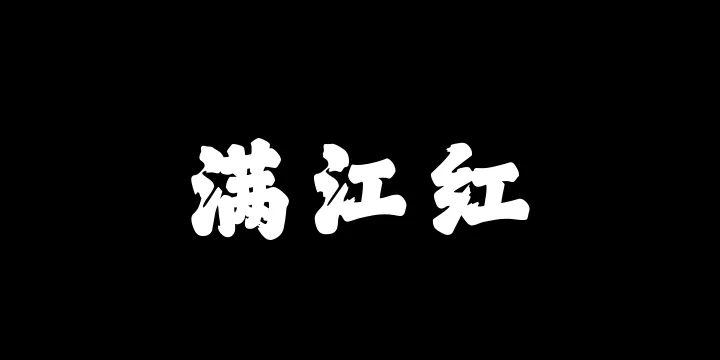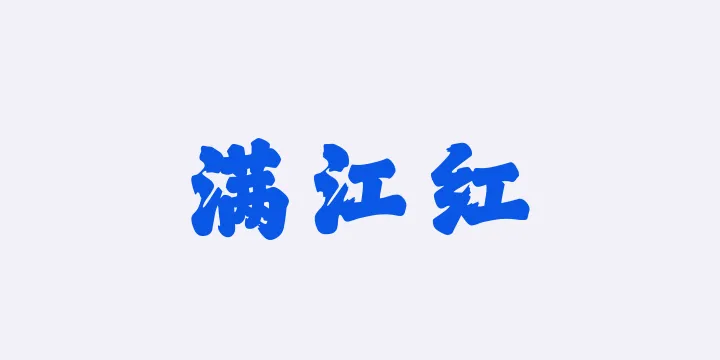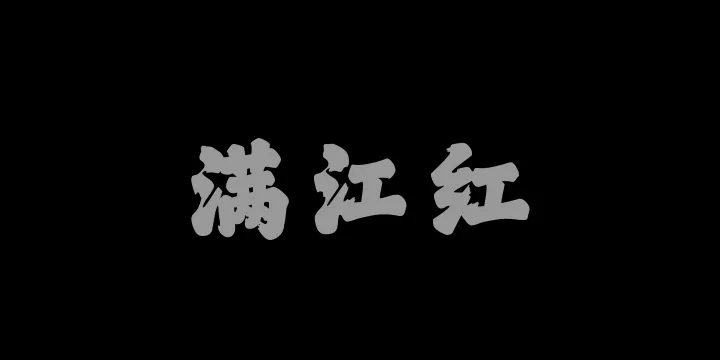
字体全名: 山海满江红W
字体简介: 山海满江红,是一款擘窠大字榜书字体。包含简繁汉字9169个。该字体雄健有力,霸气外露,在粗细的纵横间,拥有非常规的张力特性。该字体的笔画充满力量感,组合搭配极富强烈的节奏感,融入楷书特点,飞白纵横其间,使字体的视觉效果有力、宽厚、方正,充满了稳重感和设计感。笔画与字形间透露着榜书的古雅和刚劲的特点,在浑厚的同时而又极富张力,桀骜不驯的特性,霸气外露。